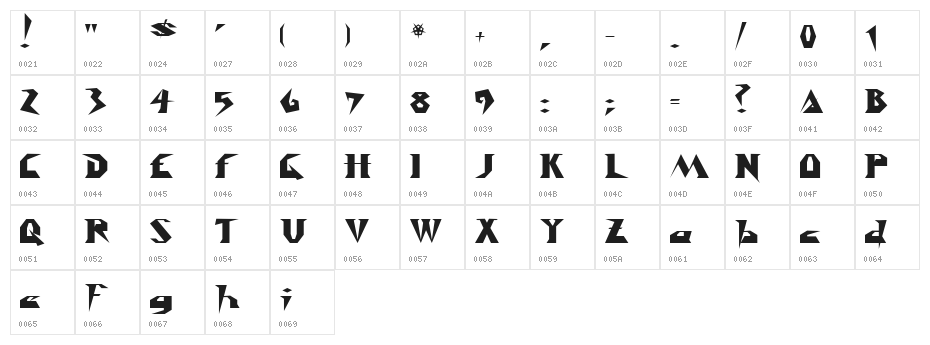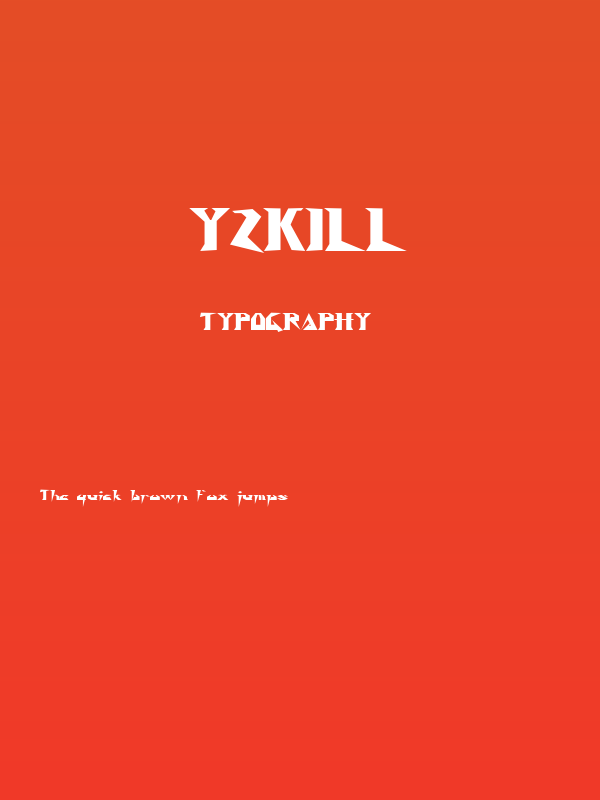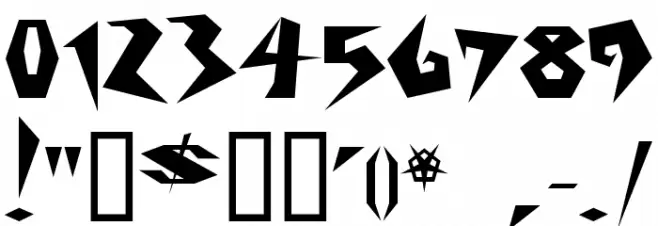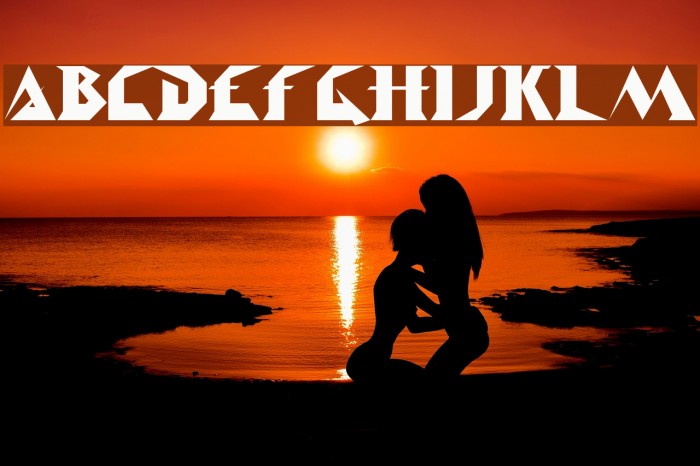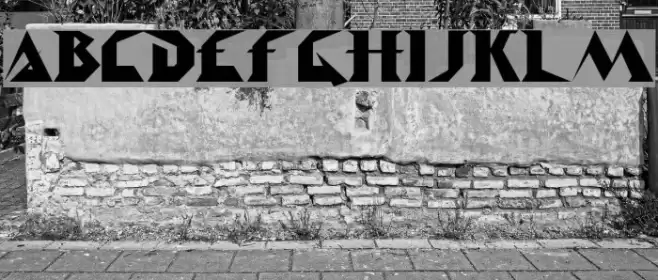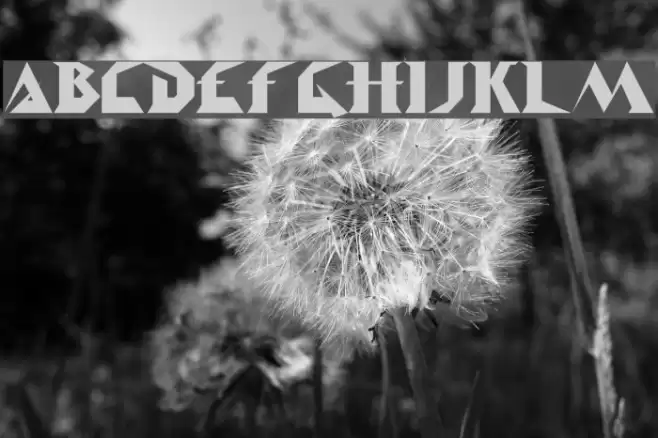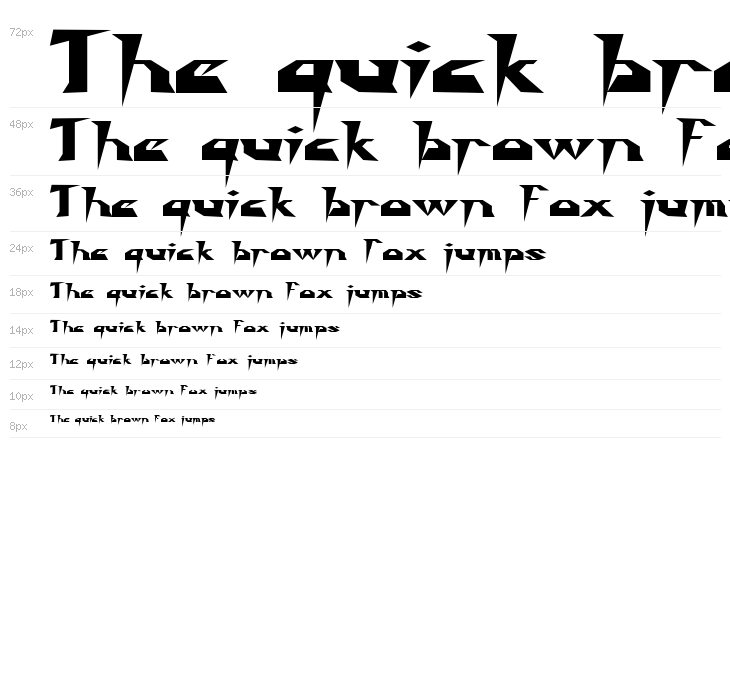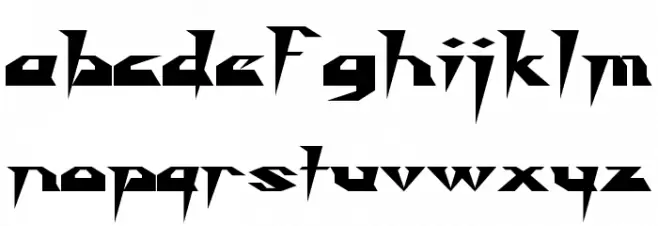
Y2Kill Font
| Proyectos propuestos | Ideal for projects that require a modern and edgy look, such as video game titles, movie posters, or branding for tech companies. |